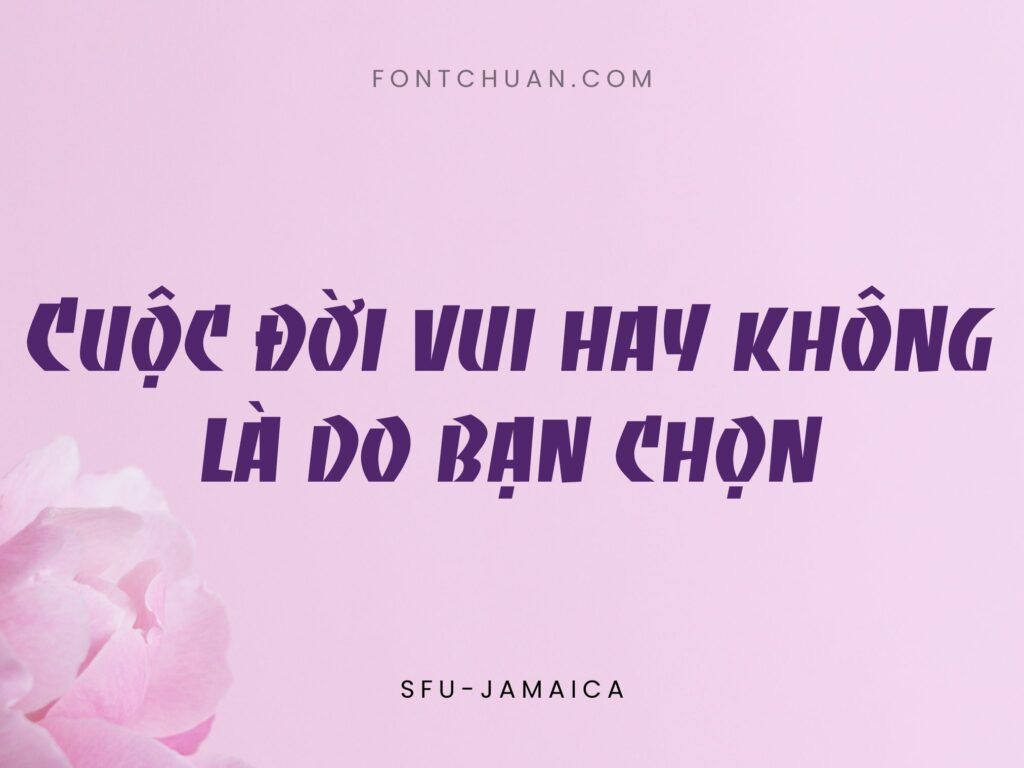
Font SFU Jamaica Việt Hóa
Jamaica là một kiểu chữ viết tay độc đáo, được thiết kế bởi Yahhya Anas và phát hành trên DaFont. Font này được sưu tầm và đăng bởi thành viên của Font Chuẩn. Với phong cách viết tay tự nhiên và sáng tạo, Jamaica tạo cảm giác phóng khoáng và nghệ thuật, phù hợp cho nhiều mục đích thiết kế khác nhau.
Về mặt thiết kế, Jamaica nổi bật với các đường nét mềm mại, uyển chuyển, tạo cảm giác gần gũi và thân thiện. Font này hỗ trợ nhiều ngôn ngữ và bao gồm các ký tự đặc biệt, giúp người dùng dễ dàng tùy chỉnh theo nhu cầu. Jamaica thường được sử dụng trong các thiết kế thiệp mời, logo, tiêu đề và các dự án cần sự sáng tạo và cá nhân hóa. Các ngành nghề như nghệ thuật, thiết kế đồ họa và quảng cáo có thể tận dụng kiểu chữ này để tạo dấu ấn đặc biệt trong truyền thông.